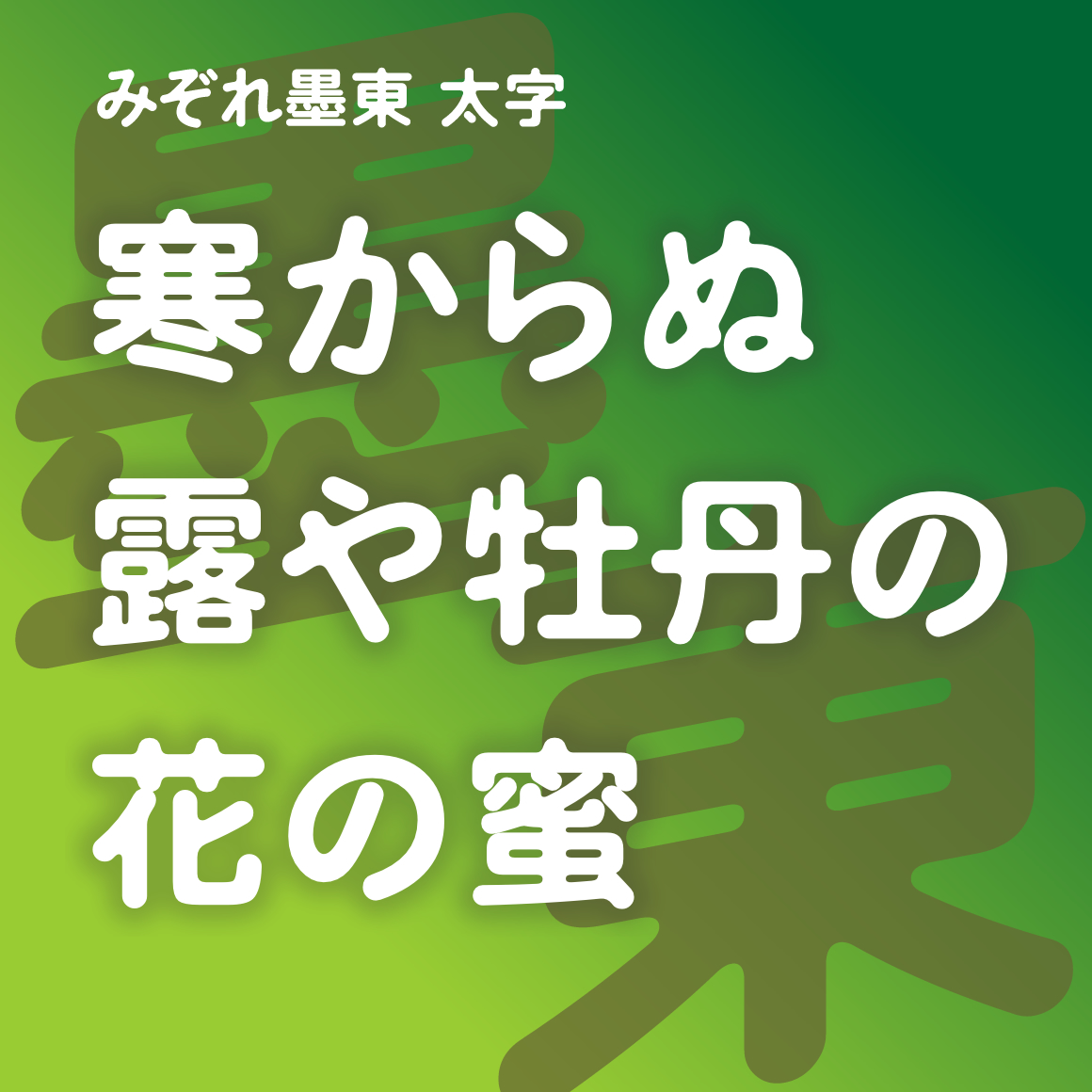
| デザイン |
線画の交点を丸くし、日本の湿潤な気候やしっとりとした感覚を、かな文字本来の字体で表した書体…。
連想されるイメージ |
湿度・湿りけ・潤い・和み・沁みる・日本人気質・以心伝心・優しさ・こころ・曖昧・情緒・しっとり・緩い・ぬくもり・柔らかい・麗し・にじみ・とろみ・ゆったり・おぼろげ・朧・はんなり・潜在意識・サブリミナル効果・梅雨・思いやり… |